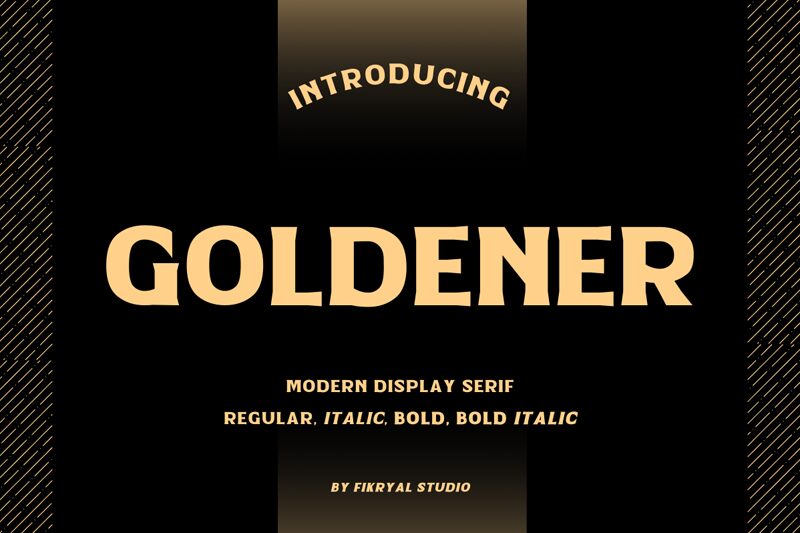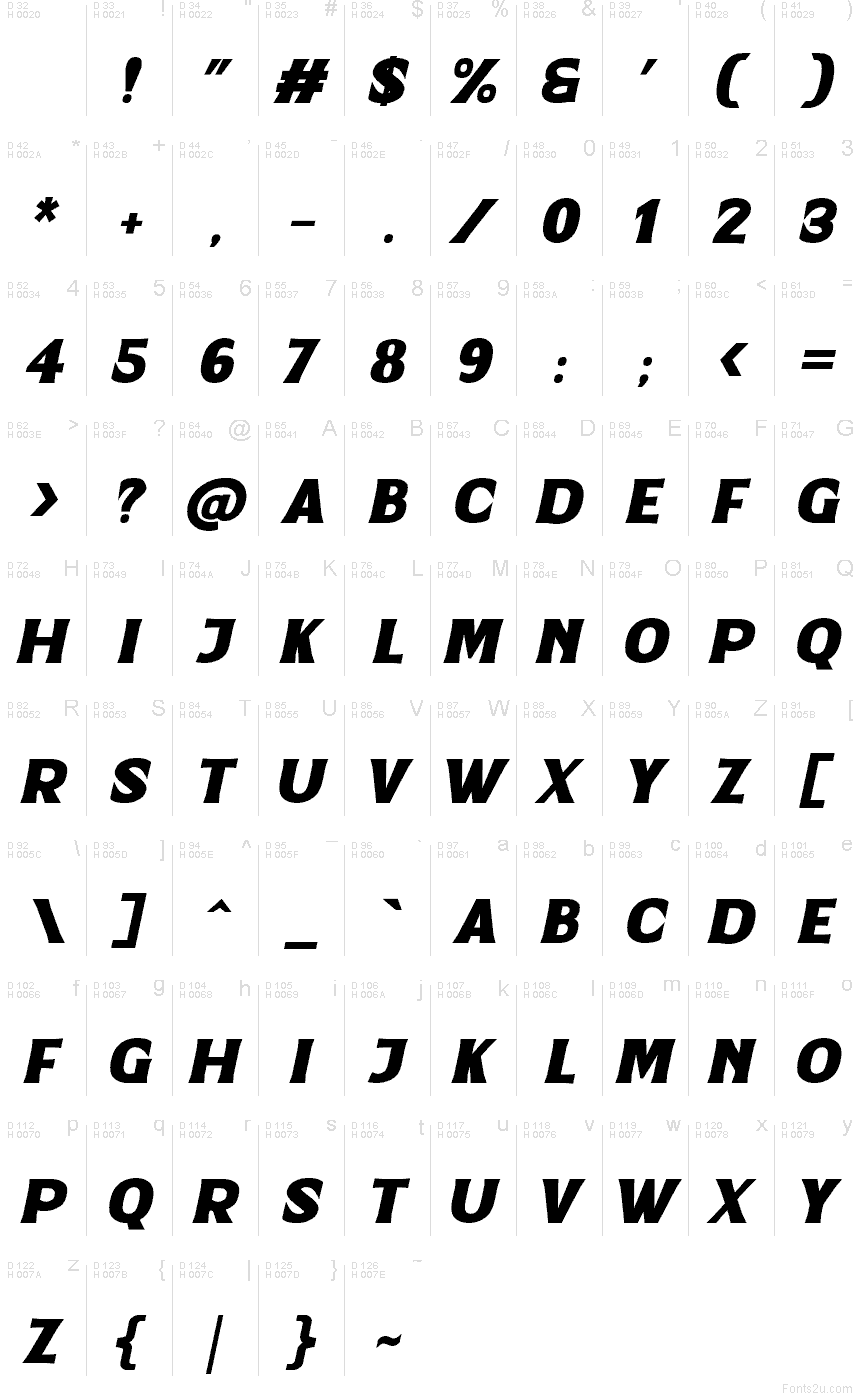
Goldener Bold Italic, creata da Muhamad Fikry Nuralif di Fikryal Studio, è un font serif corsivo della famiglia Goldener, audace e dal piglio dinamico. I tratti spessi e la spaziatura serrata creano forme robuste e fluide, che trasmettono una sensazione di velocità - come le scritte dipinte sui banner delle gare - mentre le curve ammorbidite la rendono accogliente e mai troppo aggressiva.
Goldener Bold Italic è perfetta per il branding sportivo, loghi streetwear, titoli di poster, promo di eventi, miniature YouTube, packaging di prodotti e citazioni d'impatto. Usala in grande per valorizzare la sua inclinazione e abbina questo font gratuito a un sans serif pulito e neutro per il testo secondario, così il titolo manterrà tutta la sua forza e leggibilità.